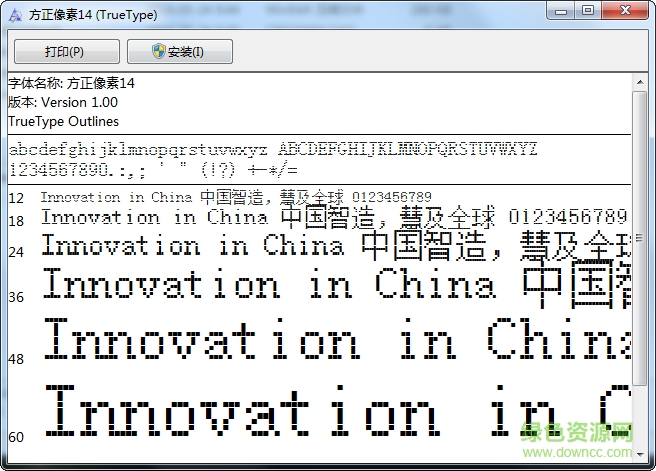
软件介绍 软件标签: 方正像素 像素字体 字体 方正像素14字体是方正像素字体中的其中一款,事实上方正像素字体各个的区别不大,增整体风格统一,只是组成的方块像素有点区别,需要下载方正像素字体14的就来绿色资源网吧。方正像素14字体安装方法方法一:控制面板/字体/文件/安装新字体;方法二:直接将字体复制到C:\WINDOWS\Fonts。注意事项本站所有字体资源仅供个人学习与参考,如需商业使用请到相关官网授权。 软件截图 上一张下一张(1 / 1) 安装详细截图 猜你喜欢 像素字体 手机像素游戏 像素字体 像素字体是一种非常有特色的字体,有中文也有英文,最主要的的特色就是它是由一像素的小方块组成的字体,这种字体在何种分辨率下都依然很想清晰,在PS中的署名、表情签之类的使用的都挺多的 查看更多>> 04b_03b 35KB/中文/5.0/下载 04b 21-普通 18KB/中文/3.3/下载 zpix字体 2.44M/中文/9.0/下载 fzxs12 gb1 0 245KB/中文/6.6/下载 可爱像素字体1.0 2.33M/中文/10.0/ttf版下载 方正基础像素字体 for mac 1.25M/中文/10.0/下载 手机像素游戏 手机像素游戏,大家可以理解为方块、颗粒游戏。因为游戏基本上是由方块或颗粒组成,看起来给人一种像素的感觉。像素游戏采用独特的怀旧画风,不想2D、3D游戏画面那样精美,但是其轮廓和色彩都非常清晰,角色造型也很卡通,这就是像素游戏的独特之处。 查看更多>> 我的世界钢铁侠模组免费 123.54M/中文/6.6/v1.75 安卓版下载 pixel studio汉化版 90.62M/中文/6.6/v4.94 安卓版下载 circle像素圆生成器 3.20M/中文/5.0/v2.2.36 安卓版下载 house像素之家 31.80M/中文/10.0/v1.0 安卓版下载 我的世界龙珠超模组整合包 513.09M/中文/6.0/v1.0 安卓版下载 其他版本下载 标题 大小 更新日期 下载 下载地址 电脑版 方正像素14 点击报错 软件无法下载或下载后无法使用,请点击报错,谢谢! 关闭报错反馈 请描述您所遇到的错误,我们将尽快予以修正,谢谢! *必填项,请输入内容 本类最新 方正粉丝天下字体 官方版 方正雅珠体简体 共8款 fzlthjw-gb1-0 方正强克体系列字体 共8款 方正字体打包合集 for Mac 苹果电脑版 方正综艺繁体字体 相关文章 Photoshop字体安装使用方法和技巧 如何解决“无法新增字体”问题 Win 7系统安装字体方法 网页字体大小设置方法 怎么改网页字体大小 在Linux系统中安装字体的几种方法 windows7字体显示问题:打开某些程序的时候显示的是乱码 用户评论 热门评论 最新评论 发表评论 查看所有评论(0) 昵称: 请不要评论无意义或脏话,我们所有评论会有人工审核. 字数: 0/500 (您的评论需要经过审核才能显示)